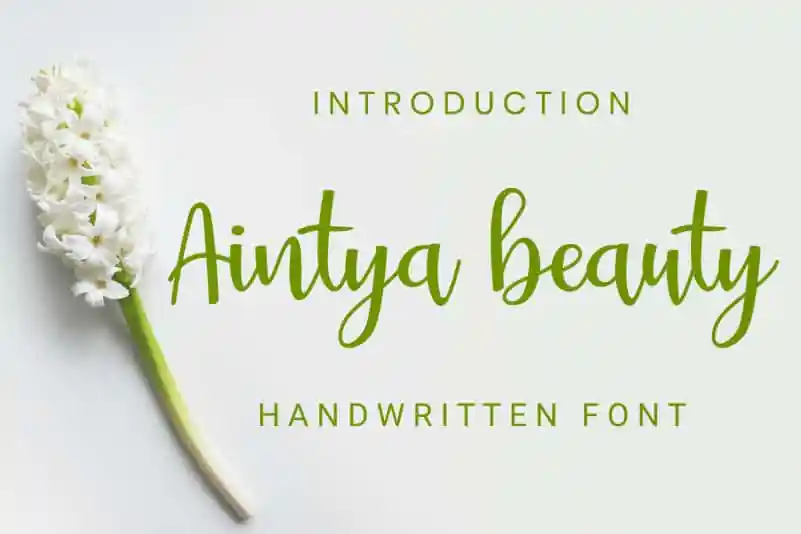
Aintya beauty Handwritten Font – Download Grátis
A Aintya Beauty Handwritten Font é uma elegante e amigável escolha para aqueles que buscam personalidade em suas criações digitais. Suave e descontraída, essa fonte está destinada a amplas aplicações de design, desde logotipos e identidades visuais até cartões de aniversário divertidos e postagens engajantes nas redes sociais. Com seu estilo relaxado, esta font é perfeita para um amplo espectro de projetos. Não hesite em usá-la em sua próxima campanha de wedding invitations ou em uma série de cartas de cumprimentos adoráveis. Também faria um excelente ajuste para estilos visuais delicados e criativos, tais como cards de festa ou até mesmo o design do seu próprio blog ou perfil pessoal. Esta font oferece a liberdade necessária para expressar sua personalidade ao criar designs únicos e incrivelmente detalhados. Seja você um designer gráfico profissional ou alguém que usa ferramentas digitais para expressar a sua criatividade pessoal, Aintya Beauty Handwritten Font está aqui para fornecer as ferramentas perfeitas.